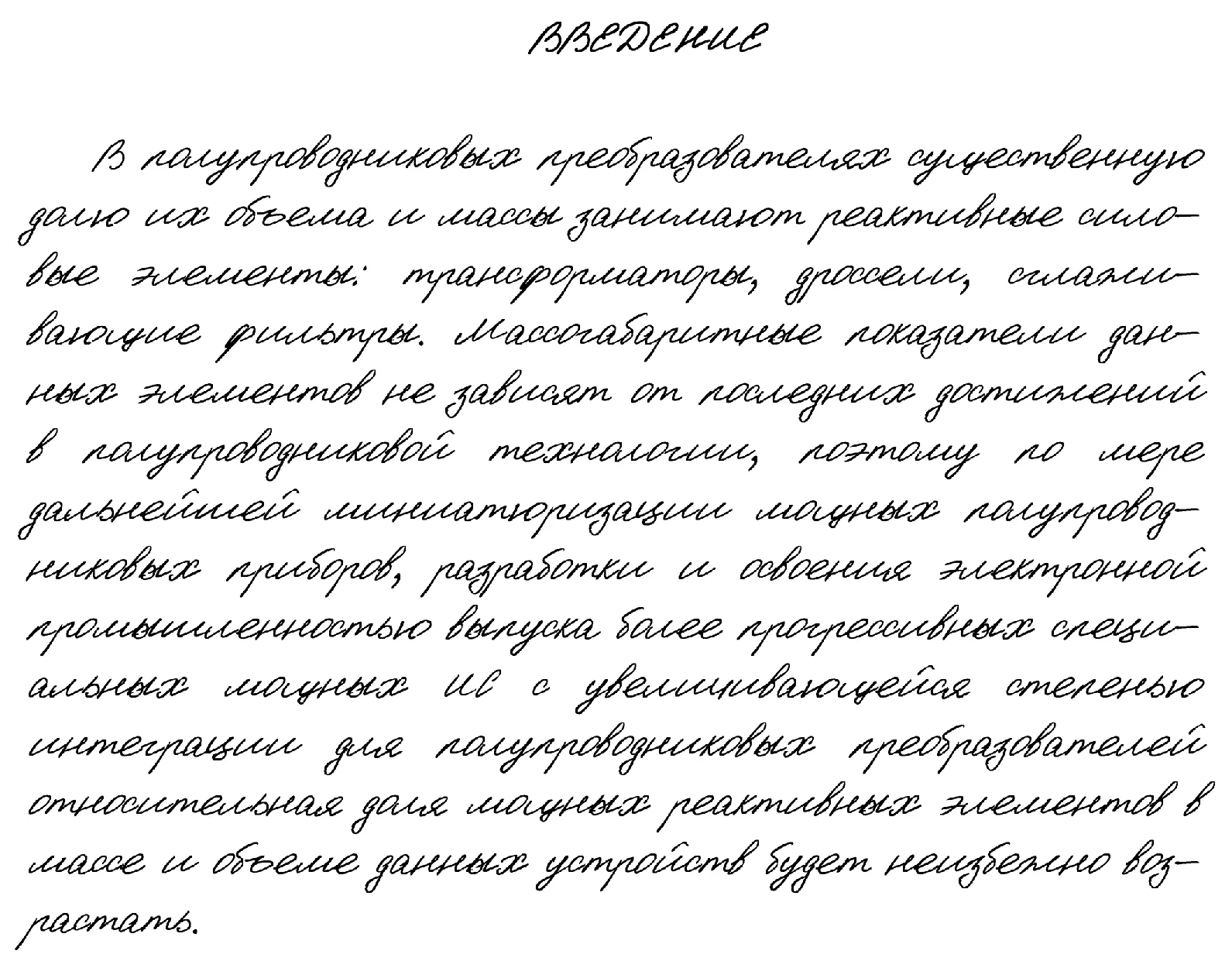
Авторский шрифт, сделанный из реального почерка человека. Благодаря данному шрифту вы сможете печатать любые нужные вам тексты, при этом они будут максимально похожи на рукописные.
Шрифт будет полезен для написания "от руки" рефератов, курсовых, дипломов, различного рода заявлений и т.д.
Поддерживаемые языки:
- русский
- английский